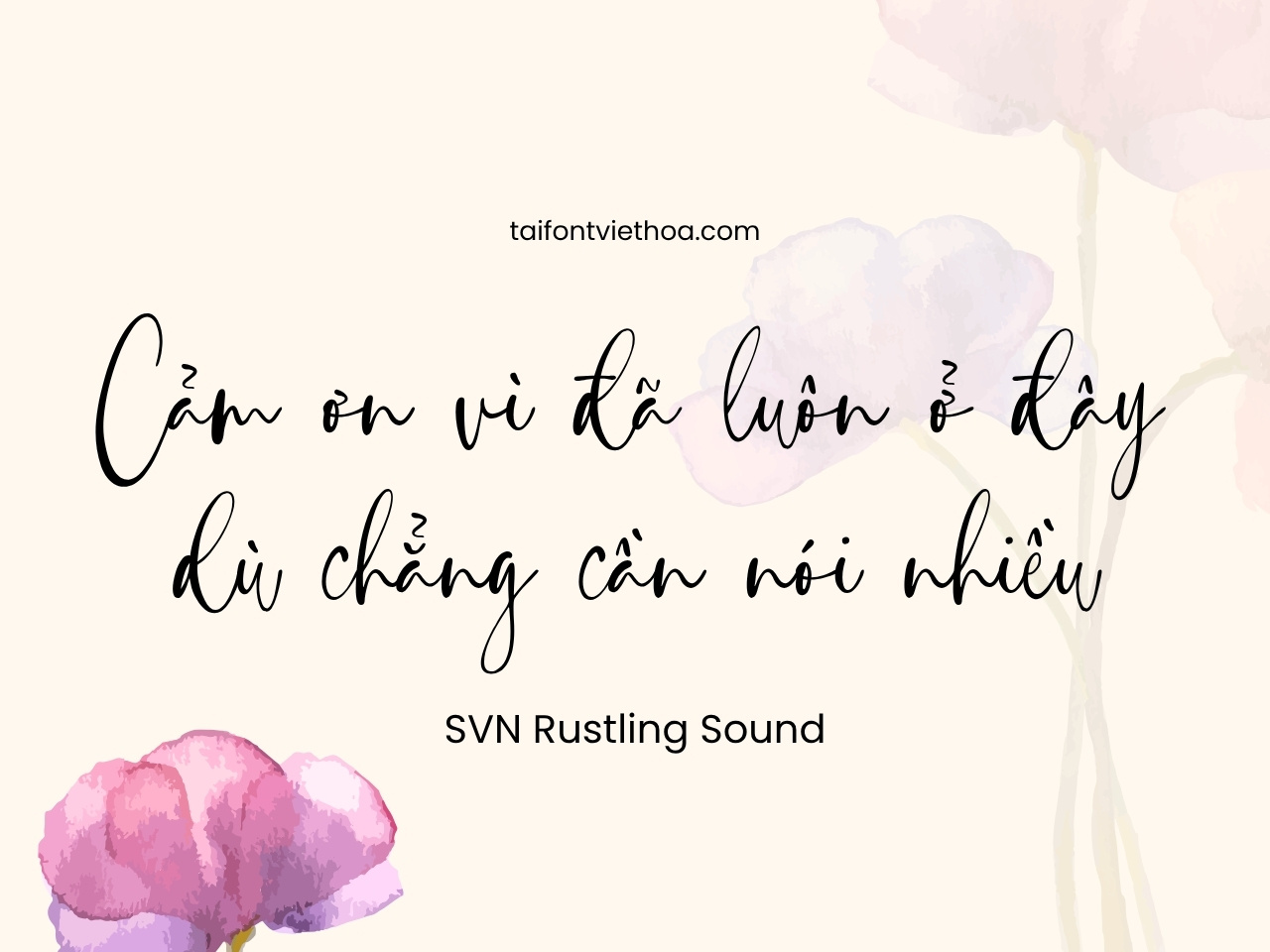
Giới thiệu về font SVN Rustling Sound – Kiểu chữ viết tay tự nhiên, mềm mại và bay bổng
SVN Rustling Sound là phiên bản Việt hóa của font Rustling Sound – một kiểu chữ handwritten mang phong cách tự nhiên, nhẹ nhàng và giàu cảm xúc. Font được thiết kế để mô phỏng nét bút lông mềm mại, uốn lượn và thoáng đãng, tạo cảm giác thư giãn và gần gũi cho người đọc. Rustling Sound thường được sử dụng trong các dự án nghệ thuật, thiệp mời, thiết kế lifestyle và các sản phẩm sáng tạo mang phong cách handmade.
Phiên bản Việt hóa do Taifontviethoa.comtuyển chọn, hoàn thiện và chia sẻ, hỗ trợ đầy đủ dấu tiếng Việt cùng hơn 70 ngôn ngữ khác, giúp nhà thiết kế dễ dàng ứng dụng trong các sản phẩm nội dung đa dạng. Font giữ nguyên nét bay bổng, tinh tế của bản gốc, đồng thời tối ưu khả năng hiển thị trên nhiều nền tảng khác nhau.
Thiết kế viết tay mềm mại – Lý tưởng cho thiệp mời, branding và thiết kế sáng tạo
SVN Rustling Sound sở hữu các nét chữ thanh mảnh, kết nối tự nhiên với độ nghiêng nhẹ nhàng và các ligature tinh tế. Font tạo nên sự hài hòa giữa vẻ đẹp thủ công và tính chuyên nghiệp, phù hợp cho tiêu đề, trích dẫn, logo cá nhân hoặc các thiết kế cần sự nhẹ nhàng, bay bổng. Đặc biệt, font thể hiện sự mềm mại và ấm áp, giúp truyền tải thông điệp một cách tinh tế và đầy cảm xúc.
Ứng dụng lý tưởng: thiệp cưới, thiệp mời sự kiện, thiết kế thương hiệu lifestyle, bao bì mỹ phẩm, bìa sách, sản phẩm thủ công, poster nghệ thuật và các dự án sáng tạo cá nhân. Ngành nghề phù hợp: nghệ thuật, thời trang, mỹ phẩm, cưới hỏi, truyền thông sáng tạo và các thương hiệu định vị theo phong cách nhẹ nhàng, tinh tế.